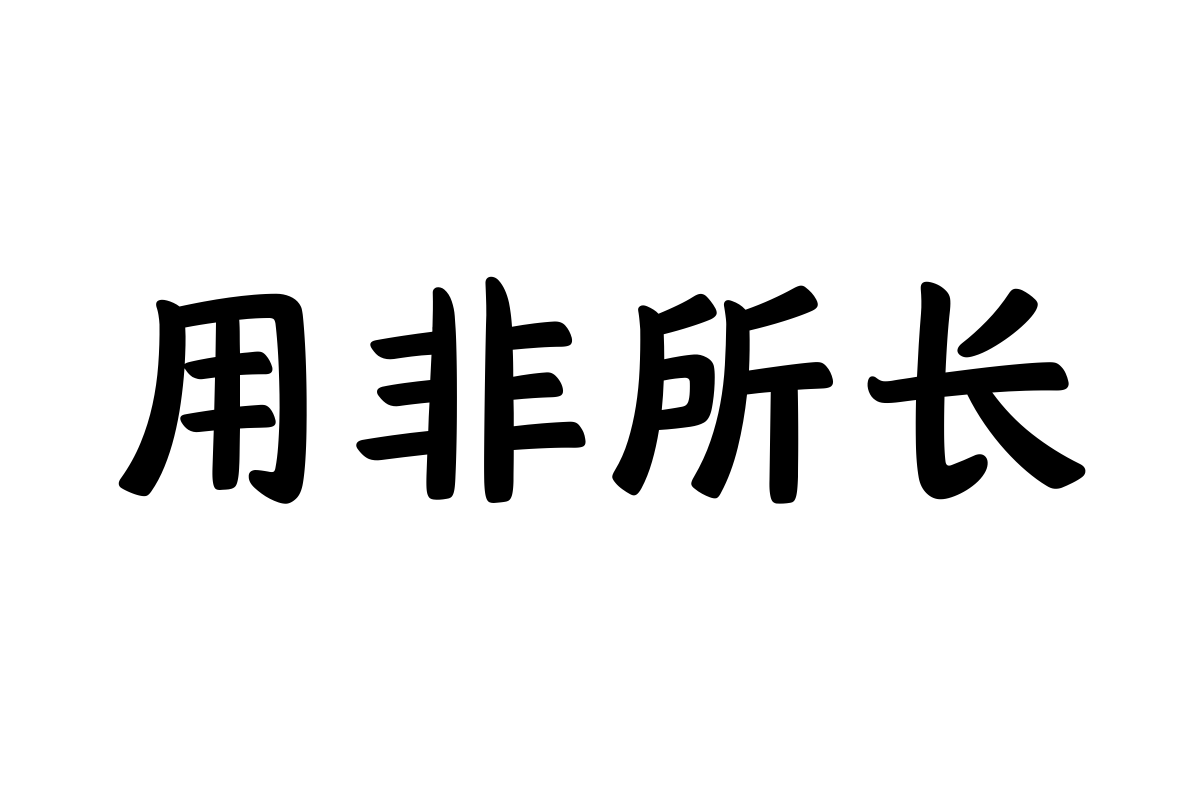
汉仪唐美人-75是一款具有独特韵味的中文字体,其设计灵感来源于唐代美人的优雅气质。这款字体笔画流畅,结构紧凑,给人以古朴典雅的感觉。在视觉上,它能够很好地展现中文的韵味和美感,适合用于各种与中国传统文化相关的设计项目。
汉仪唐美人-75的特点如下:
1. 字形美观:该字体线条流畅,结构紧凑,整体呈现出一种古朴典雅的风格。无论是书写还是印刷,都能展现出中文的韵味和美感。
2. 风格独特:汉仪唐美人-75的设计灵感来源于唐代美人,因此它在风格上具有一定的独特性。这使得它在众多中文字体中脱颖而出,具有较高的辨识度。
3. 适用范围广泛:由于其独特的风格和美感,汉仪唐美人-75适用于各种与中国传统文化相关的设计项目,如广告、包装、书籍封面等。
4. 易于使用:汉仪唐美人-75的字形规整,笔画清晰,使得用户在使用时更加方便。同时,该字体还提供了多种字重和字号选择,满足不同设计需求。
总之,汉仪唐美人-75是一款具有独特韵味的中文字体,其设计风格独特,适用于各种与中国传统文化相关的设计项目。